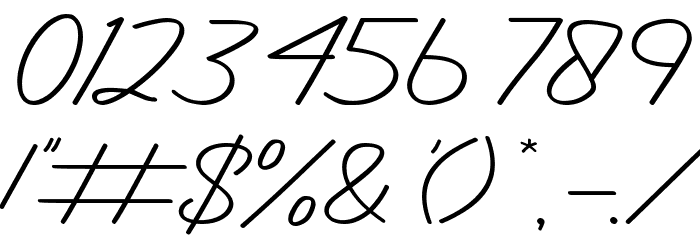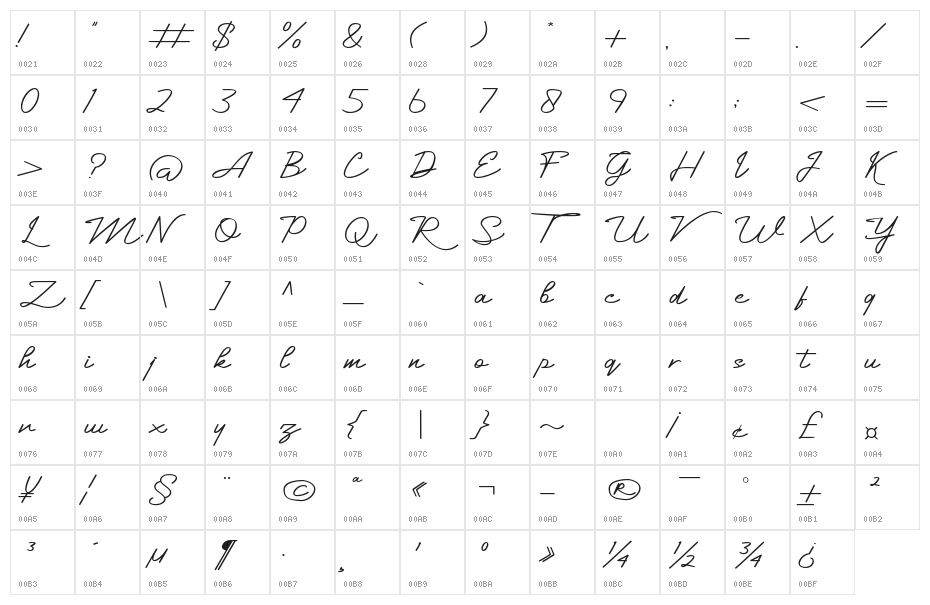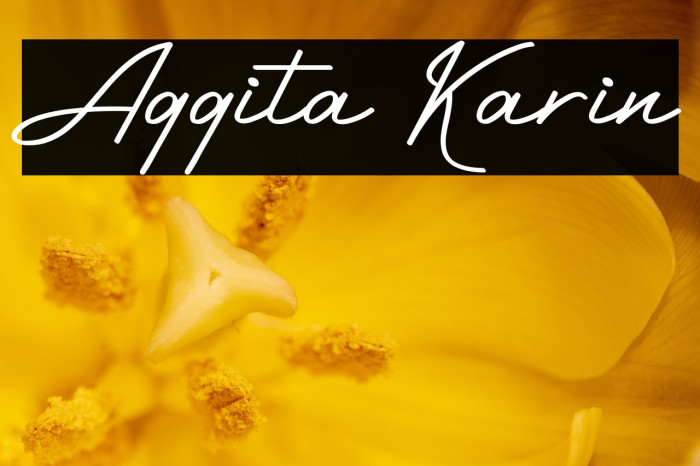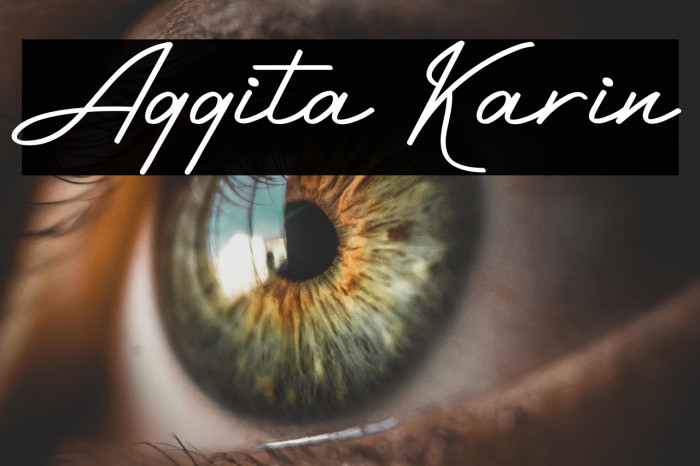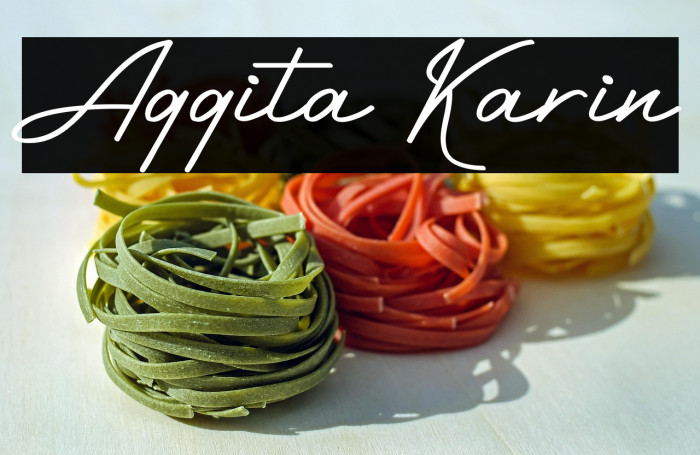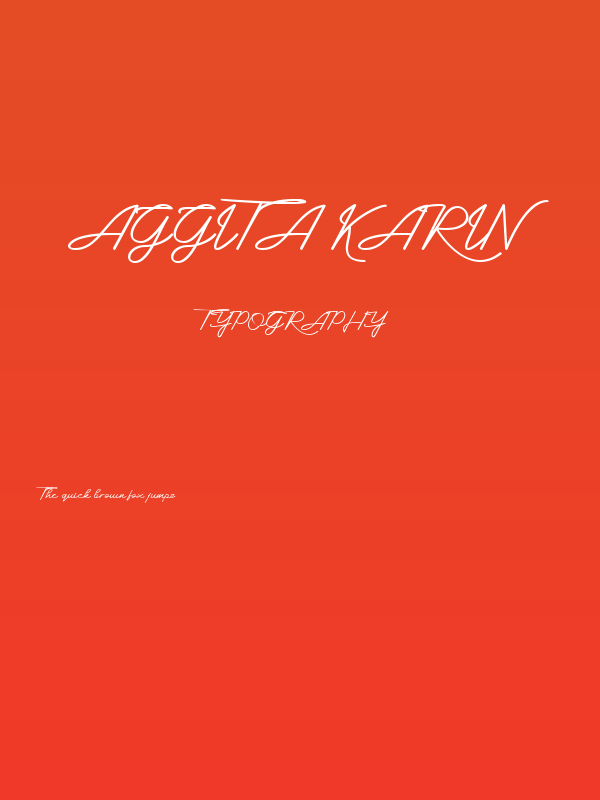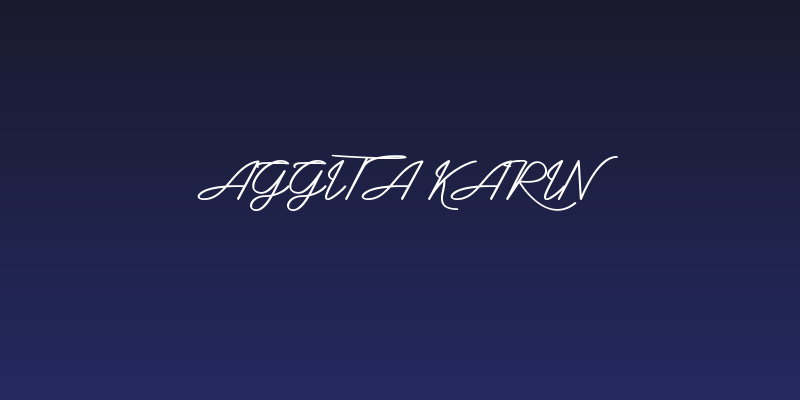
Aggita Karin Font
| Общий стиль | Elegant, Sophisticated |
| Область применения | Logos, Invitations, Branding |
| Рекомендуемые проекты | Ideal for wedding invitations, elegant branding, personal stationery, and high-end product packaging. |